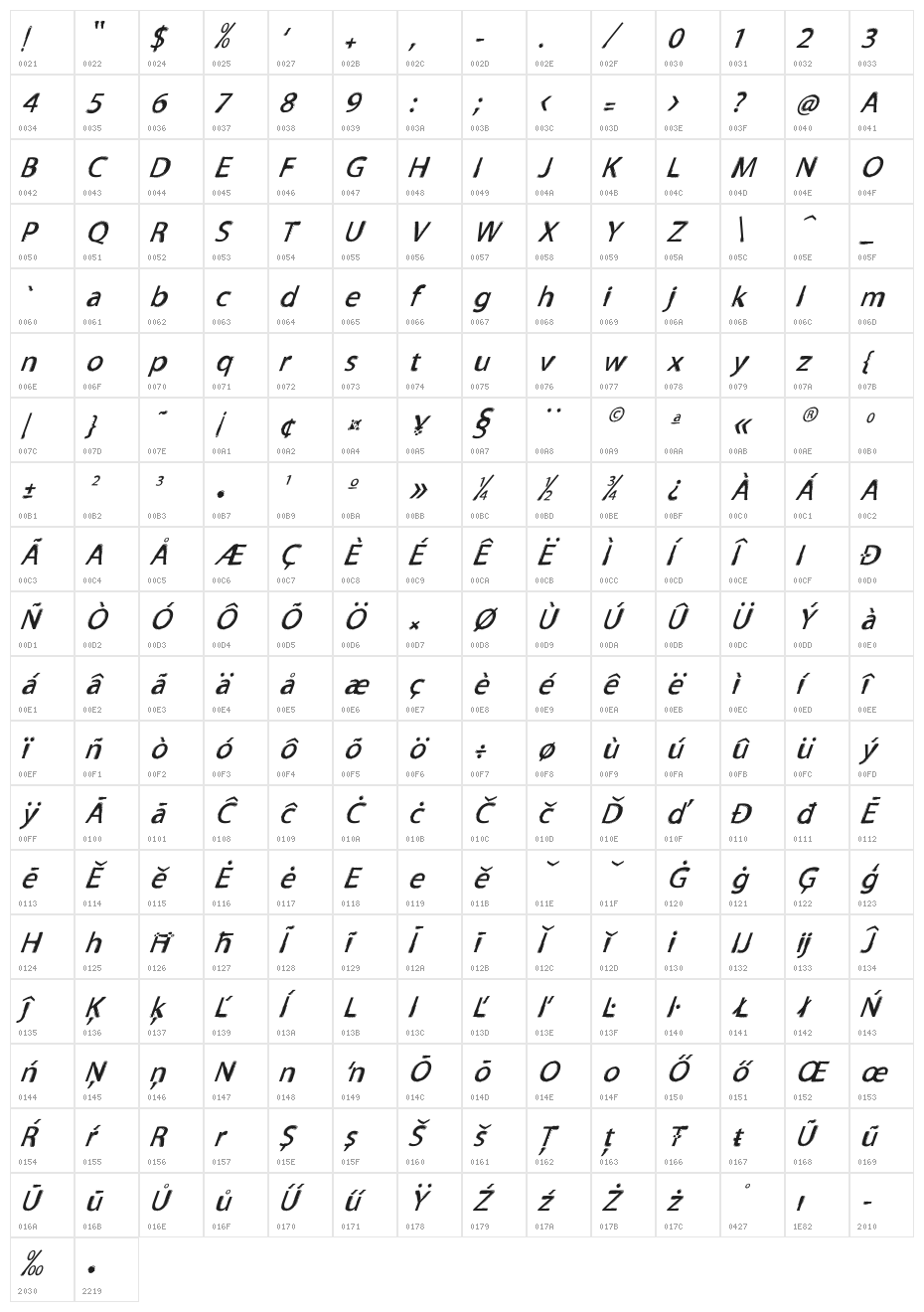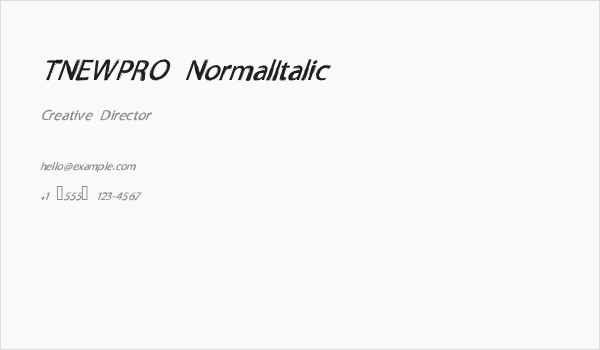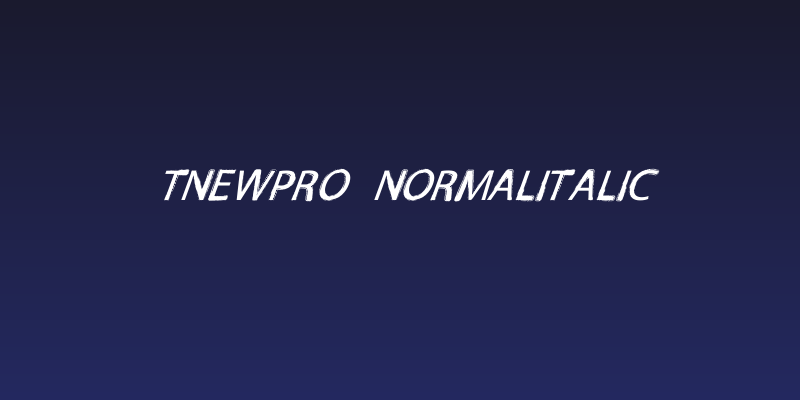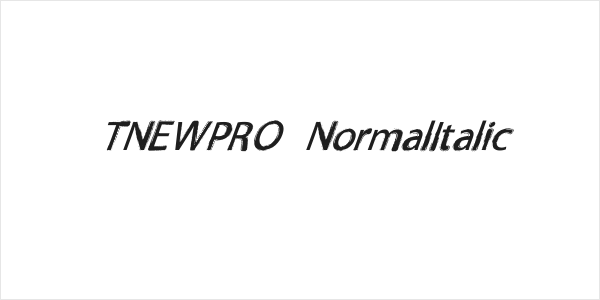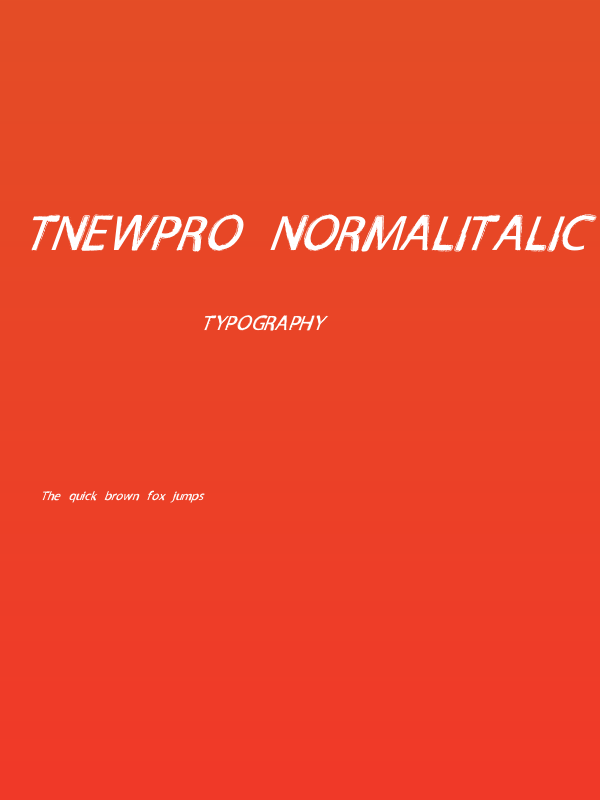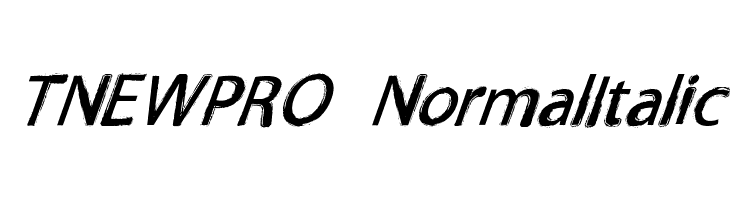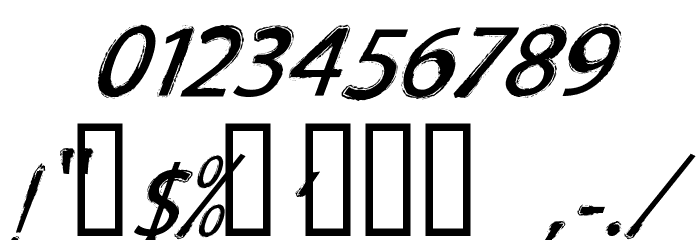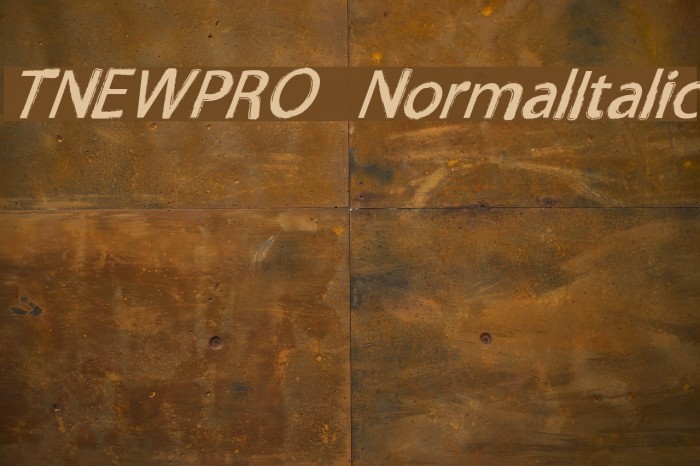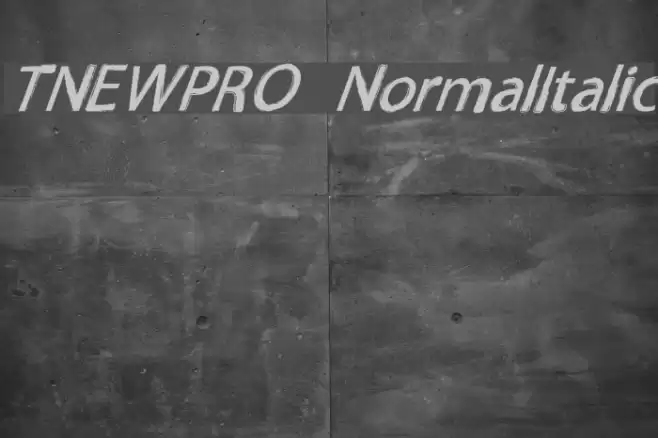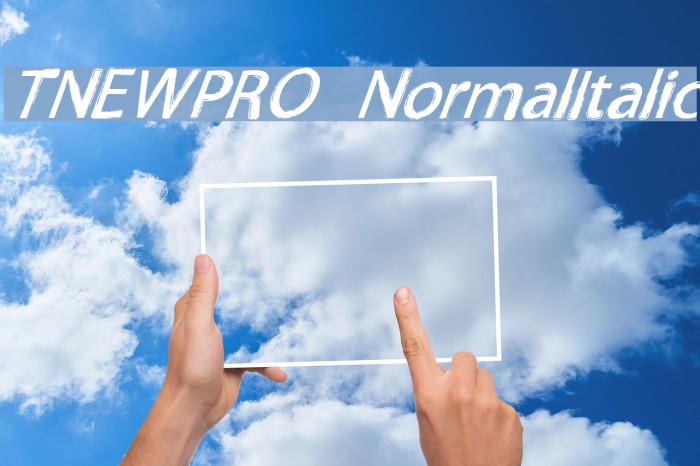
TNEWPRO NormalItalic Font
✎ Distorted Eroded
| Cas d'utilisation | Headlines, Logos, Advertising |
| Projets proposés | This font is perfect for branding, advertising, and editorial design. It can be effectively used in headlines, posters, and digital media where a modern and energetic look is desired. |